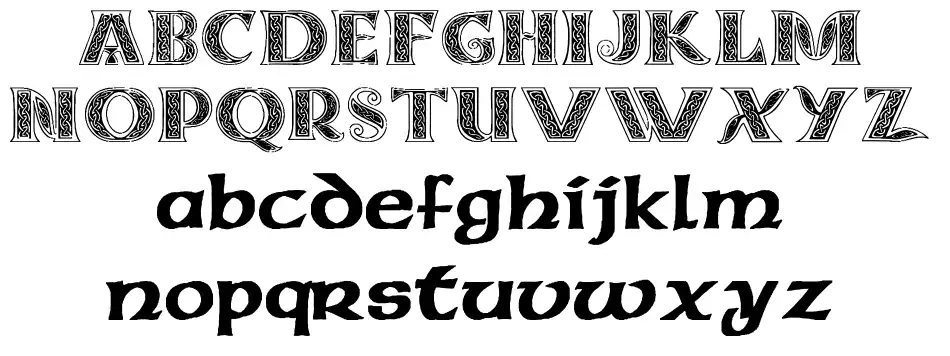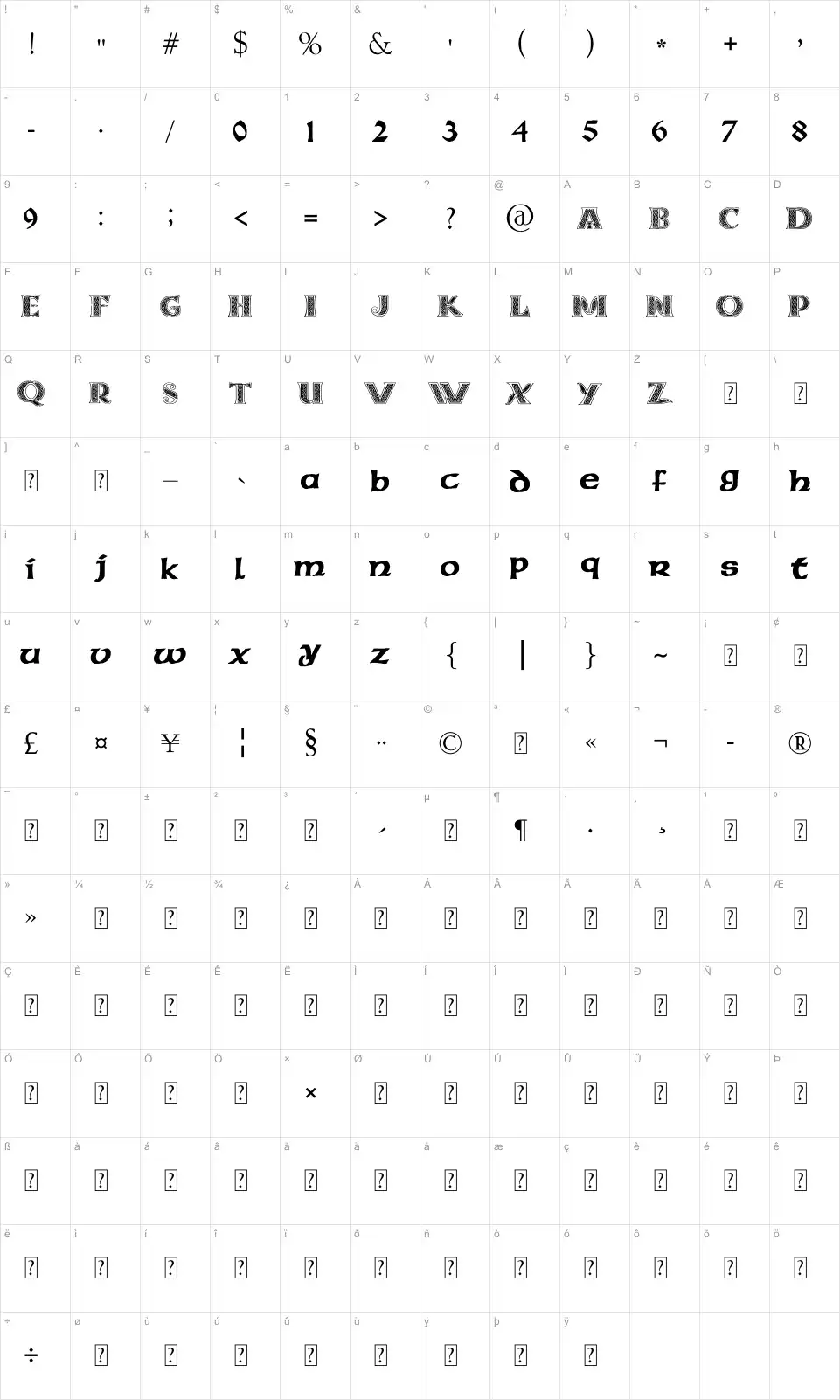
Pauls Celtic Font 3 – Download Grátis
A fonte Pauls Celtic Font 3, criada pelo designer Paul, é uma delícia para quem aprecia estilos góticos e celtas. Esta fonte é particularmente interessante para quem busca uma mistura única de elegância e charme, ideal para rótulos de produtos, marcas de loja, e até mesmo para decorar cartões de aniversário. Com uma licença de doação, qualquer um pode adquirir e usar a fonte, tanto para fins pessoais quanto comerciais. Formato TTF, ela é compacta e fácil de usar, ocupando apenas 90 KB no seu sistema. Adicionada em 12 de julho de 2022, esta fonte já teve mais de 6750 downloads, o que indica a sua popularidade e qualidade. Para ter uma ideia do que a fonte pode oferecer, é possível gerar um preview personalizado online antes de fazer o download e começar a usar a fonte no seu projeto. Visite o site do designer, ViciousInk.net, para mais detalhes e informações.